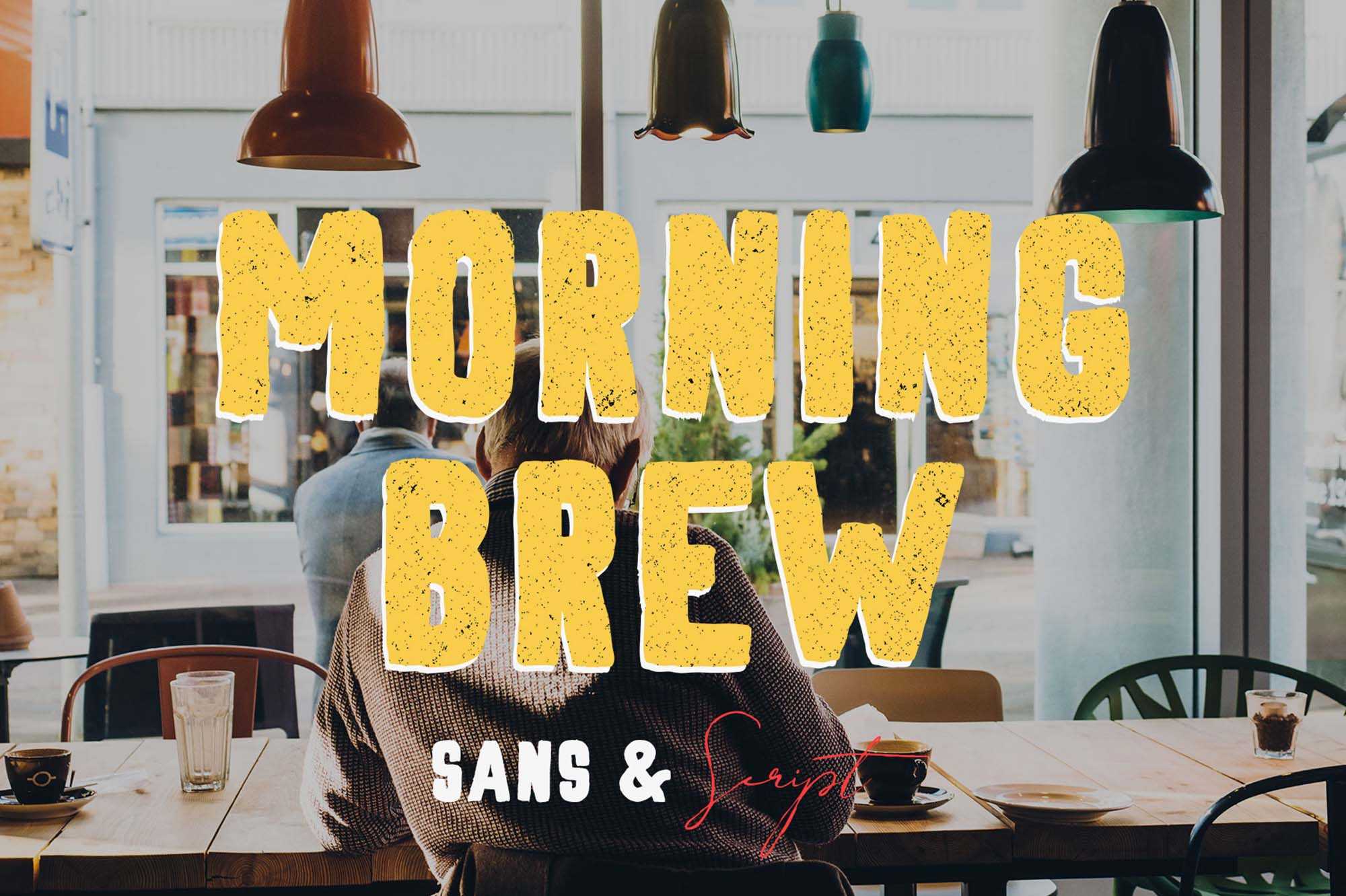
Morning Brew Hand Painted Font – Download Grátis
Morning Brew Hand Painted Font
A Morning Brew Hand Painted Font é um recurso gráfico que traz a essência do café da manhã, capturada em uma forma artesanalmente pintada. Este recurso é ideal para designers de interfaces de usuário que buscam capturar o encanto do aroma e da frescura de um bom café da manhã. Os amantes do café reconhecem o prazer do aroma fresco do café, mesmo que não sejam entusiastas de café. Essa fonte de café foi projetada com cuidado para transmitir essa sensação única, oferecendo uma variedade de opções para decorar textos e interfaces de usuário, desde os nomes de cafés até as instruções de preparo. A Morning Brew Hand Painted Font é perfeita para designers que procuram uma fonte que reforça a conexão especial que muitos têm com o café da manhã.